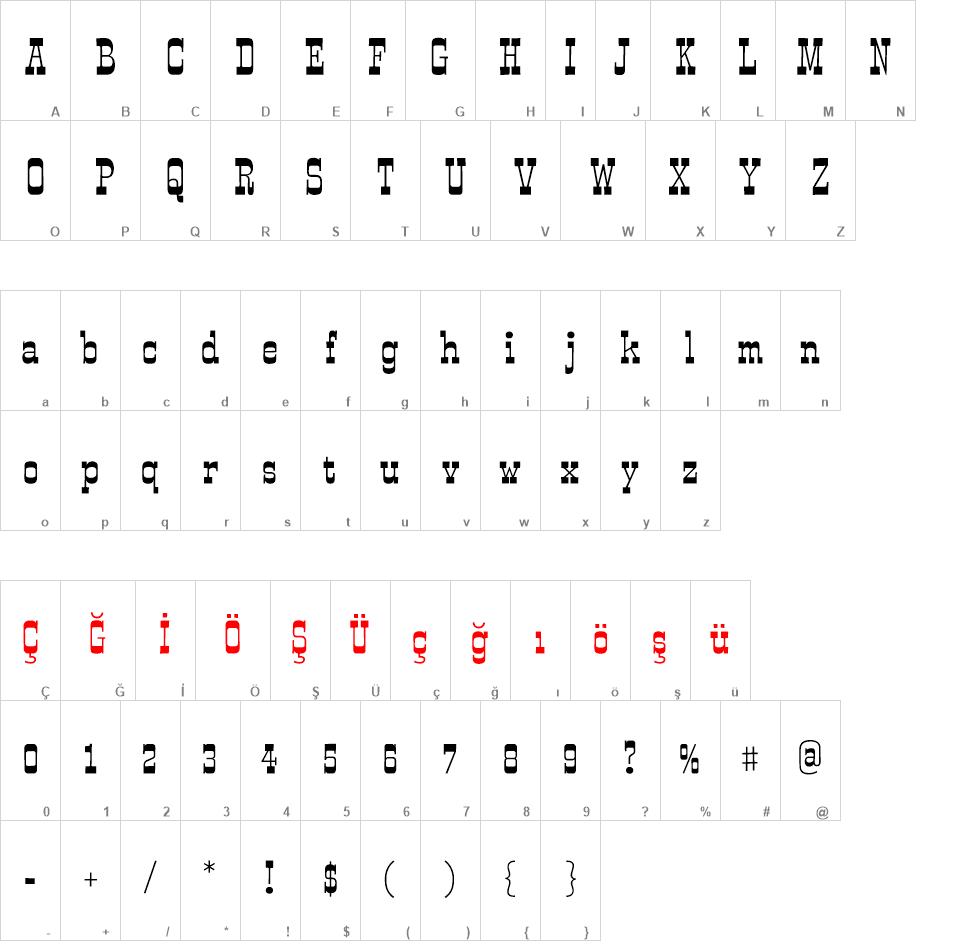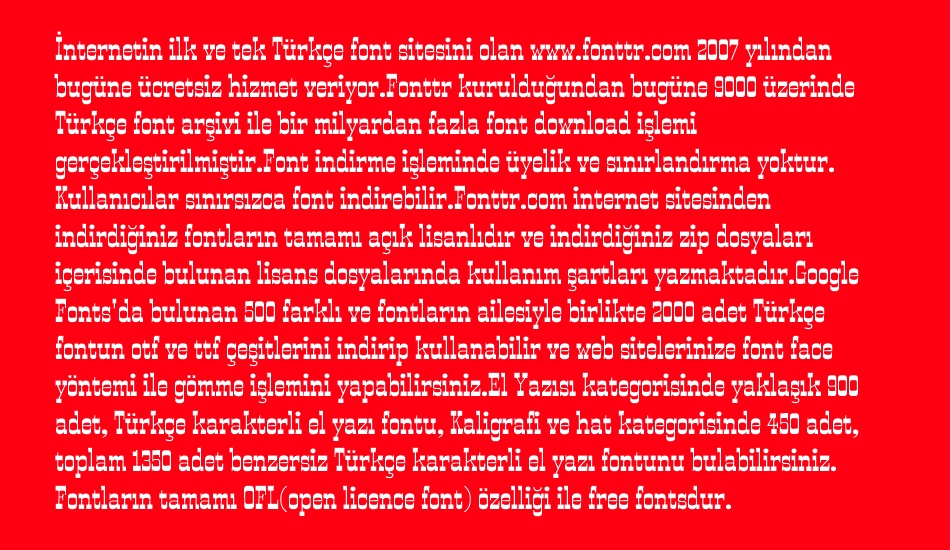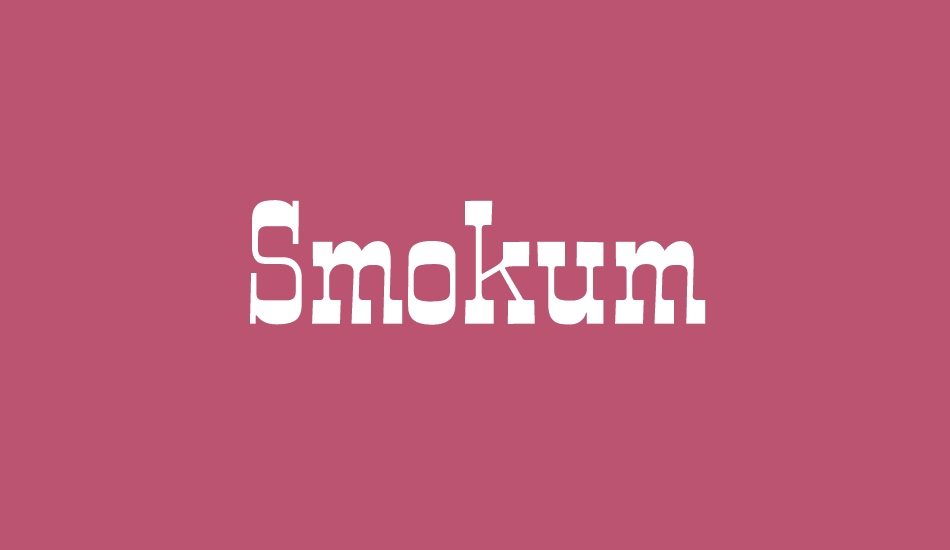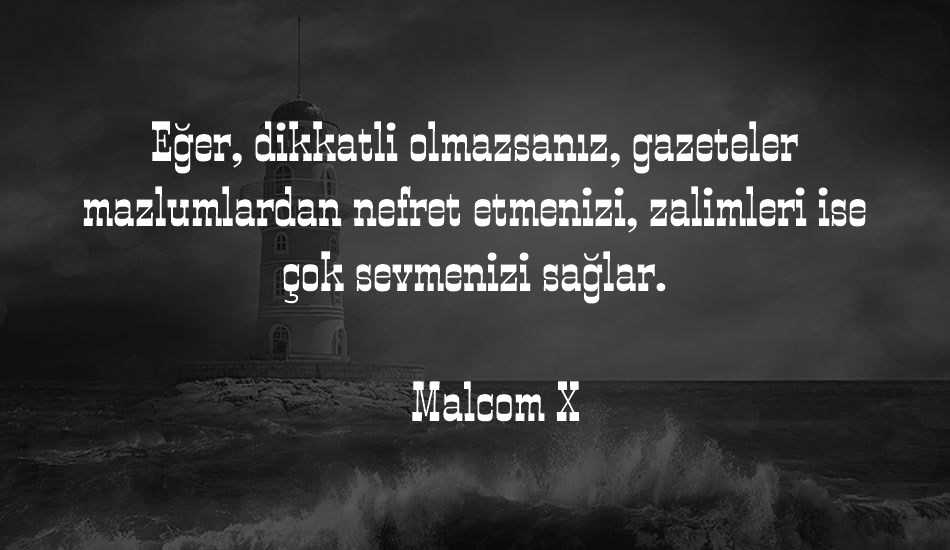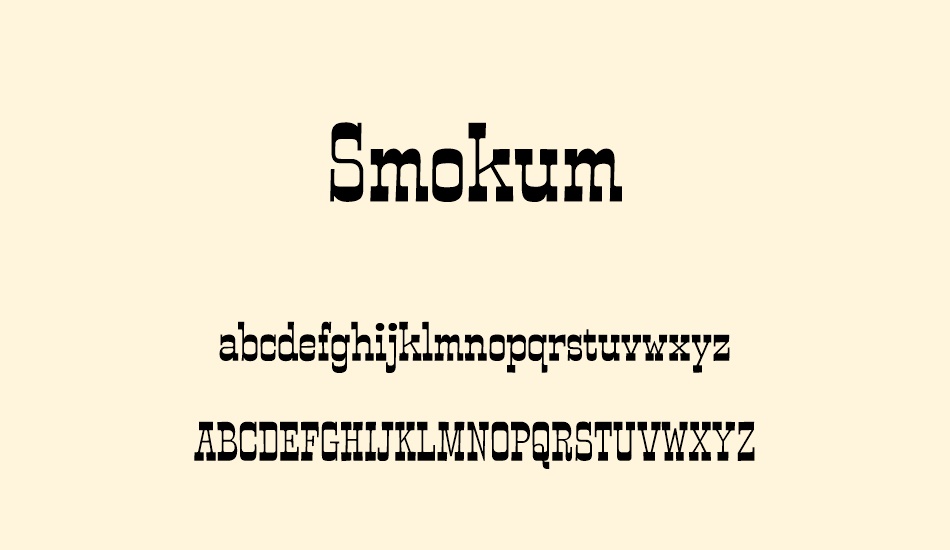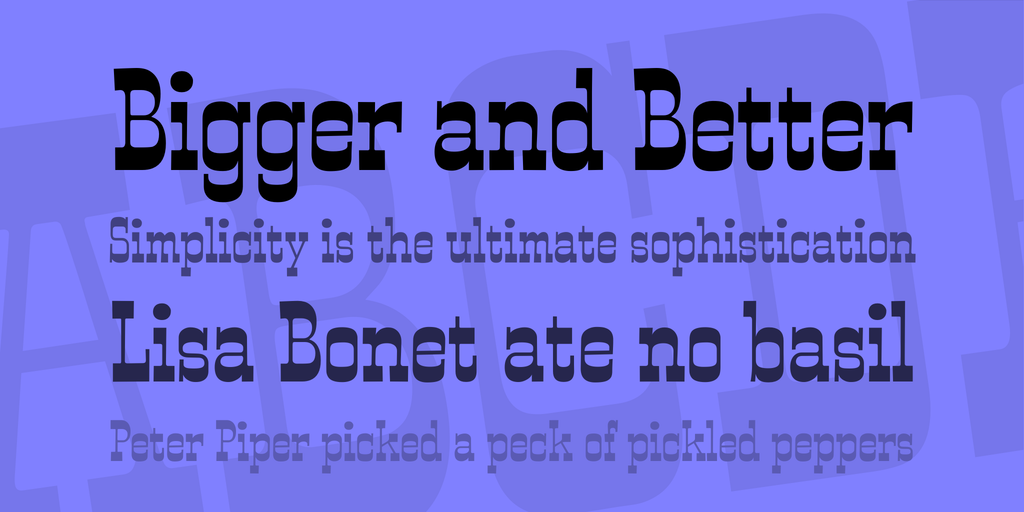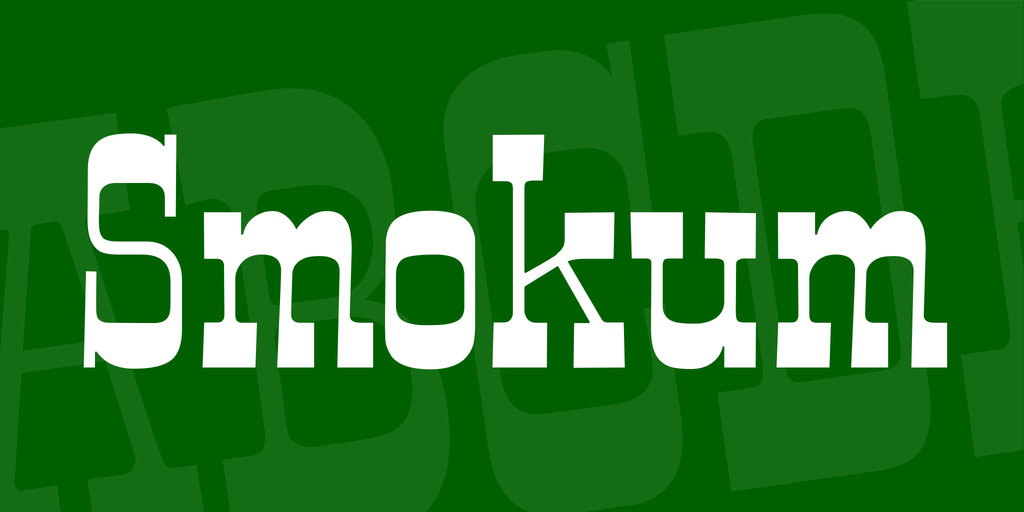
Smokum font
Smokum, batıdan esinlenilmiş, slab-serif bir yazı tipi olup, küçük eğlencelidir. Biraz gevşemiş ülke zerafeti gerektiren manşetlere ve ekran kullanımlarında mükemmel, ancak kalınlıkların ve incelticilerin zıtlığından dolayı, orta ve büyük nokta boyutlarında WebFont olarak en iyi performansı alacaktır.